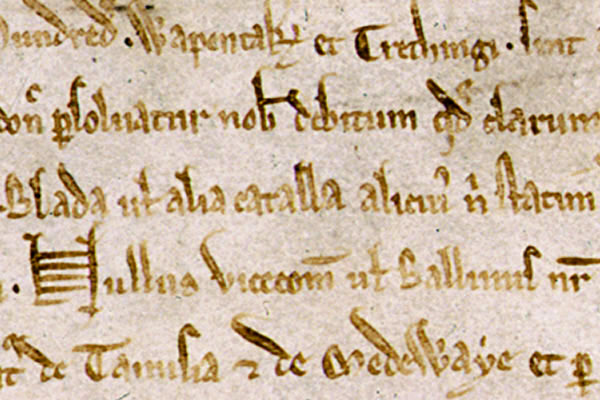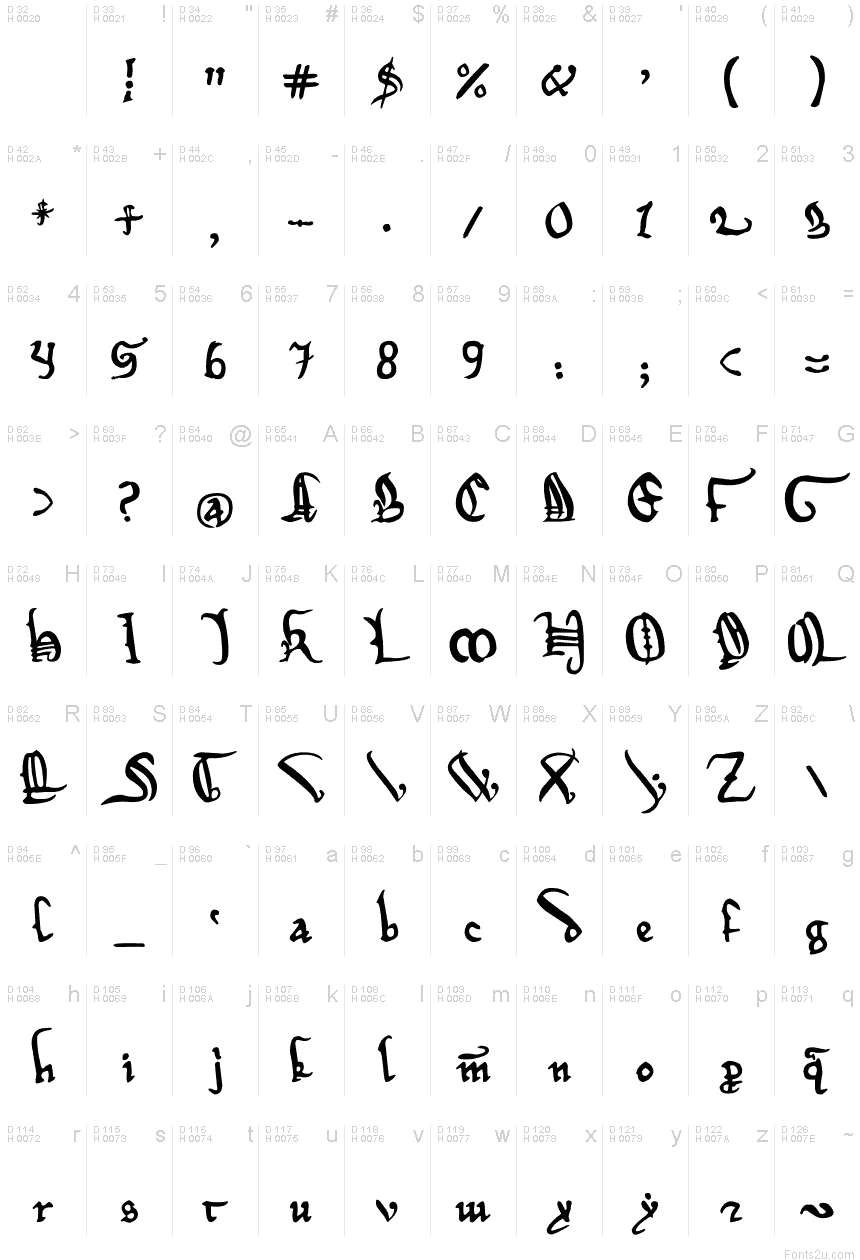
Magna Carta è un font gotico gratuito caratterizzato da forme blackletter arrotondate e un flusso calligrafico che mantiene le lettere unite senza risultare rigide. Le forme fondono tagli netti e affilati con ampi tratti curvi, conferendo al design un carattere medievale che rimanda ai documenti antichi.
Magna Carta è perfetto per certificati, copertine di libri, inviti di nozze, titoli di poster e branding araldico, grazie alle sue forme che richiamano un tono formale d'altri tempi. Questo font gratuito si adatta bene anche a loghi, avvisi per eventi e scritte decorative quando si desidera un tocco storico che risulti decorativo senza essere eccessivamente sfarzoso.
Presentazione e campione visivo del carattere Magna Carta
Mappa dei caratteri di Magna Carta
Mappa dei caratteri di Magna Carta: Latino di base, pagina 1
Glifi del carattere Magna Carta — Latino di base, pagina 1